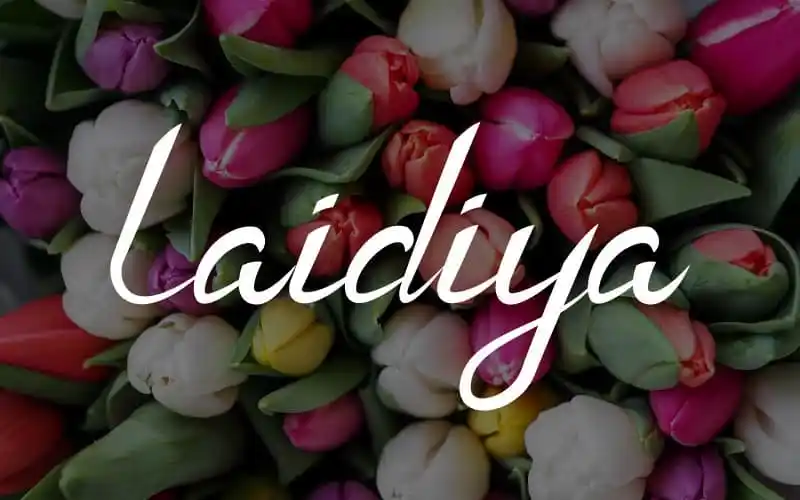
Laidiya Handwritten Font – Download Grátis
Laidiya Handwritten Font é uma elegante fonte escrita a mão com toques suaves e amigáveis. Seu estilo descontraído a torna ideal para uma ampla gama de projetos gráficos, desde logomarcas e identidades corporativas até cartões de convite casais, arte de papelaria bela e postagens de mídias sociais chamativas. Ela também é perfeita para cartazes de boas-vindas criativos e emotivos. Seja você um designer que busca uma fonte escrita a mão para seus projetos pessoais ou profissionais, Laidiya Handwritten Font será sua escolha ideal.